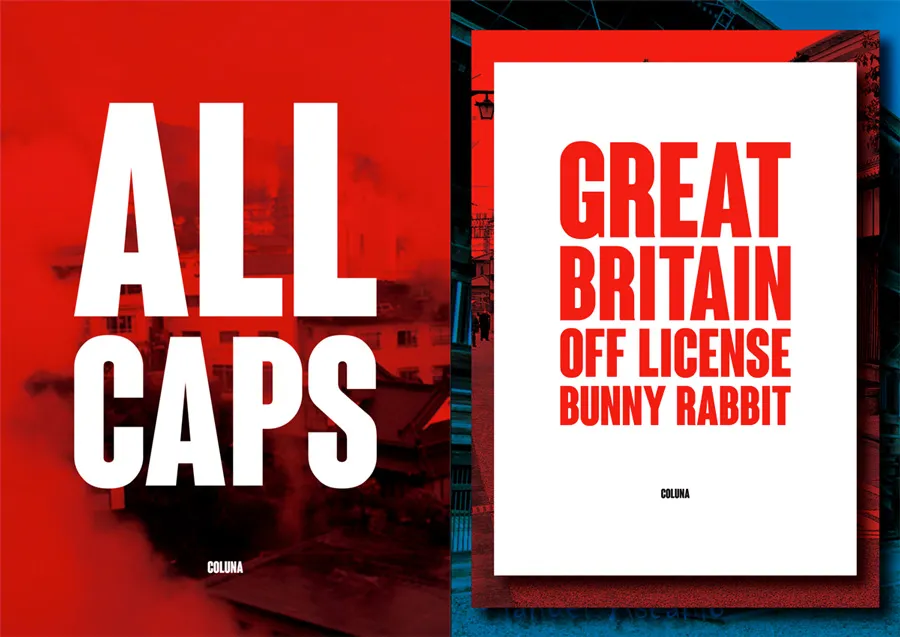
A Coluna Family Font é uma delassemelhança sutilmente bold e condensada que combina força visual com elegância. Inspirada na carreira notável do histórico jogador de futebol Mario Coluna, a fonte se destaca como um poderoso instrumento para headlines, títulos, declarações e até mesmo comerciais. Suas linhas esculpidas e seus espaçamentos reduzidos criam uma aparência contemporânea e moderna que complementa perfeitamente qualquer design gráfico. Esta fonte é perfeita para quem busca um estilo sutil mas poderoso, combinando simplicidade com robustez. Ideal tanto para criações digitais quanto para projetos impressos, a Coluna Family Font oferece uma maneira única de destacar sua mensagem em qualquer projeto visual.